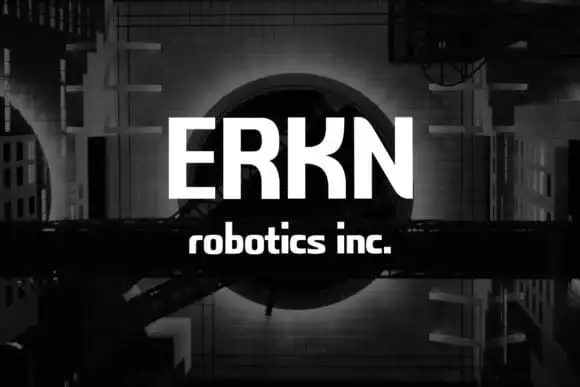
A Erkn Sans Serif é uma fonte de tipo aberto inspirada nos estilos futuristas e tecnológicos atuais e futuros. Desenvolvida para criar desenhos que se adaptam perfeitamente a designs modernos, esta fonte não só oferece um estilo contemporâneo para seu projeto, mas também garante uma ligação perfeita com ferramentas de design como o Photoshop ou Illustrator. Com suporte completo para todos os caracteres da Europa, a Erkn apresenta um conjunto de pontuação e sinais diacríticos que tornam suas aplicações ainda mais precisas e detalhadas. Este tipo aberto também está estritamente compatível com diversos programas de design modernos, incluindo openType fechado ligações e kerning ajustáveis, permitindo maior controle sobre a aparência do seu projeto. Com uma tipografia geométrica que transmite uma sensação elegante e tecnológica ao mesmo tempo, a Erkn Sans Serif é uma excelente opção para qualquer tipo de projeto. Seja para um design clássico ou moderno, esta fonte oferece estilo e facilidade de uso compatível com ferramentas digitais avançadas. Especialmente adequada para projetos que valorizam a simplicidade e a funcionalidade dos desenhos tecnológicos, a Erkn Sans Serif é uma excelente adição à sua biblioteca de recursos gráficos.